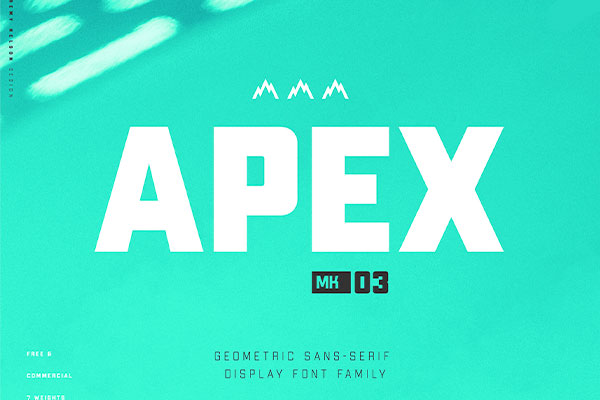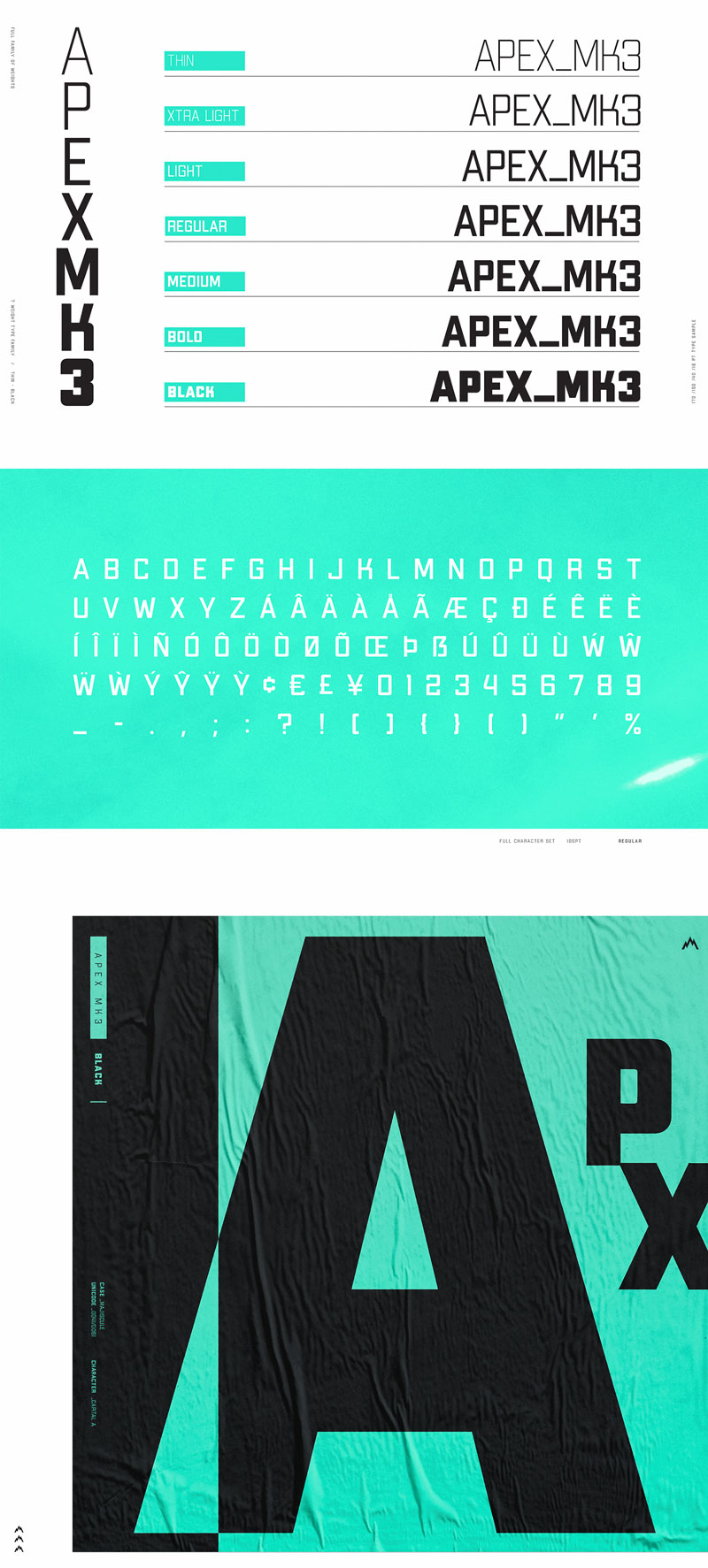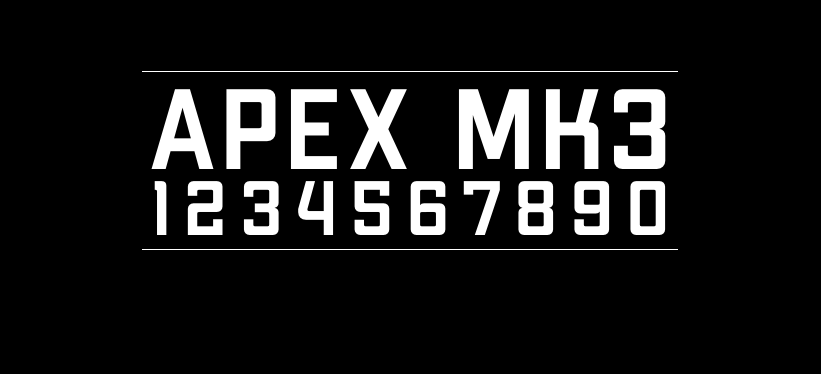
Apex Mk3
Apex Mk3字体介绍
Apex Mk3是来自Jeremy Nelson Design的一款英文字体,是通过经典的几何形式,SANS衬线,和主力运动块类型启发鲁棒显示字体。它的简单性使其具有广泛的用途灵活性,而其几何框架为其决定性的色调奠定了基础。
Apex Mk3字体应用示例